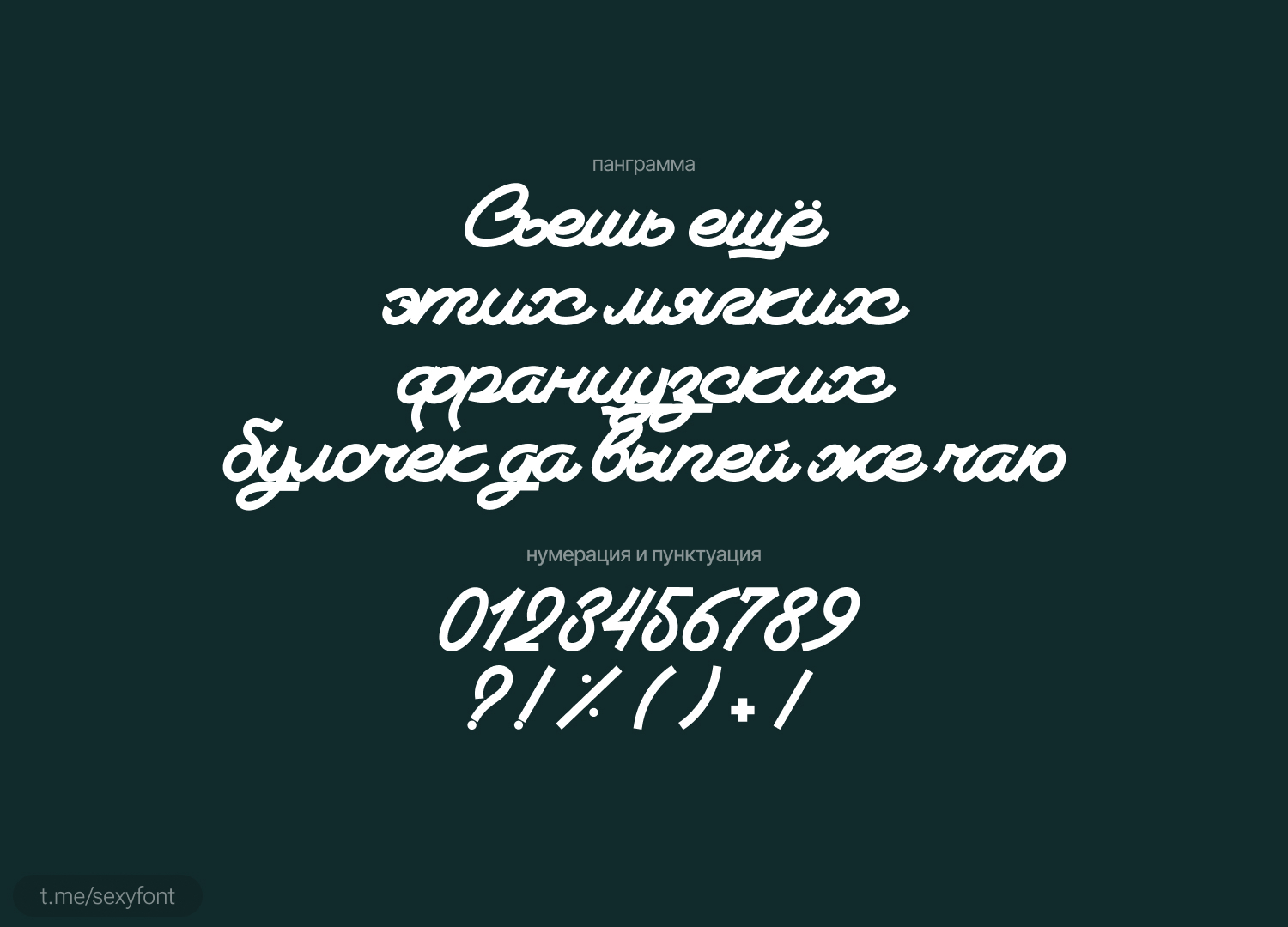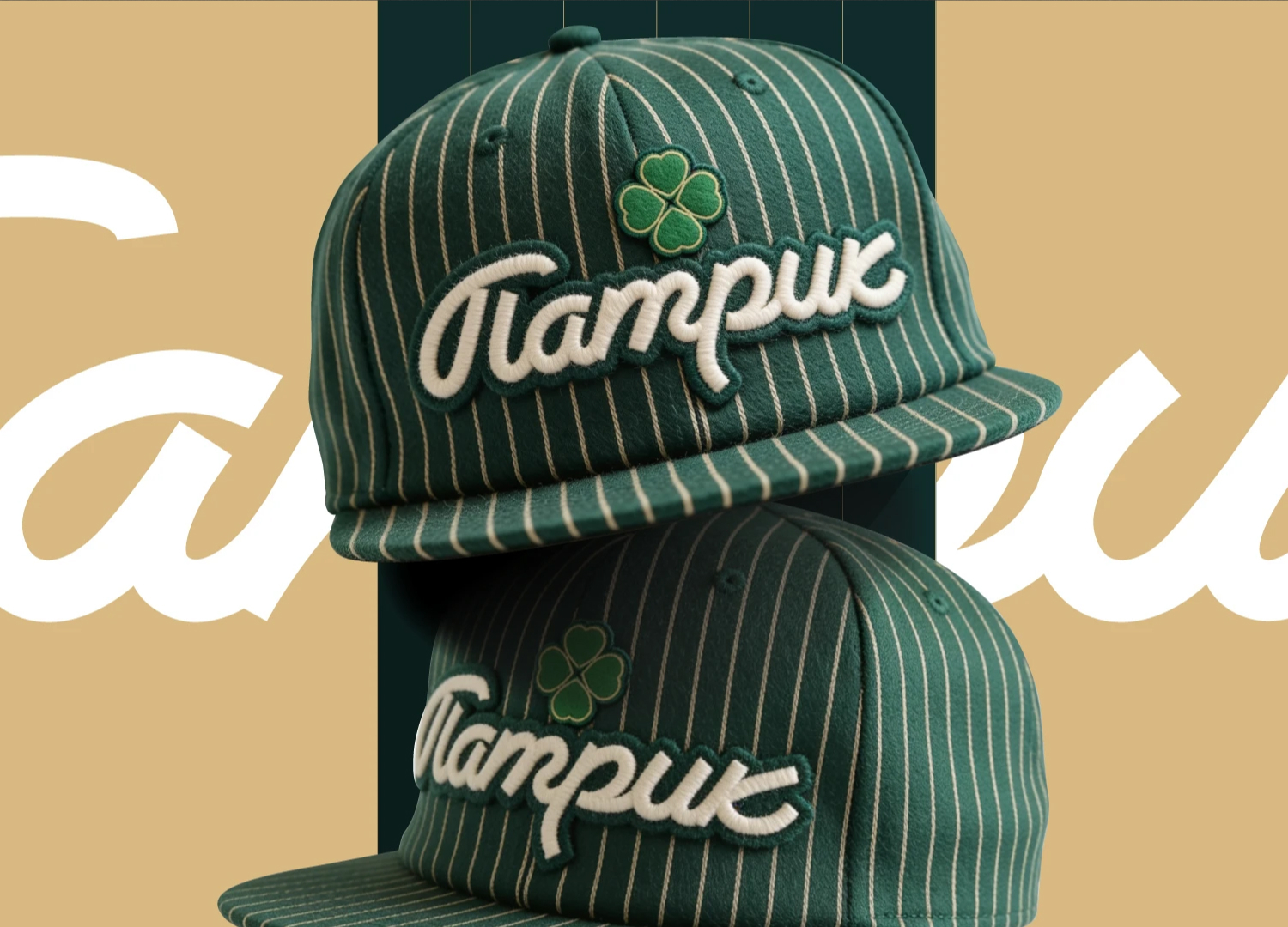
Шрифт Lemonade129⁠⁠
Шрифт Lemonade129. Красивый акцидентный шрифт в ретро стиле, вдохновлен рукописными вывесками для магазинов 40х
Автор: Vadim Bashlakov